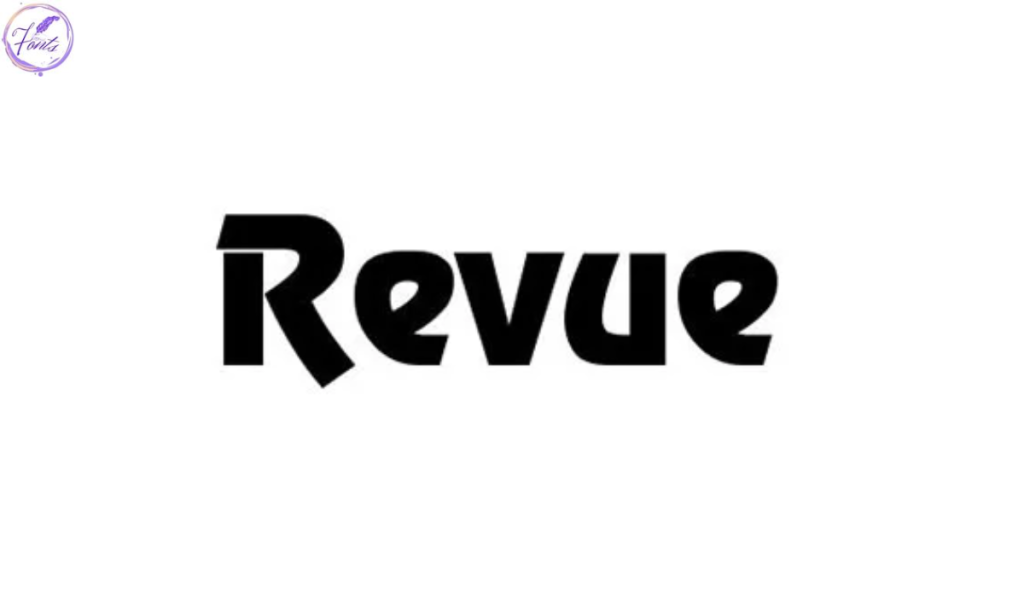
Tác giả: ITC
Ngày phát hành: 2004
Ngôn ngữ: Tiếng Việt, Tiếng Anh, và nhiều ngôn ngữ khác
Bộ Font: Revue
Phân loại: cá tính, độc đáo
Kiểu chữ: sans serif
Revue Font là một bộ font chữ độc đáo và sáng tạo, mang đậm phong cách cổ điển và hiện đại. Được tạo ra bởi đội ngũ thiết kế nổi tiếng là ITC vào năm 2004, Revue Font mang đến sự kết hợp hài hòa giữa các đường nét mềm mại và góc cạnh sắc sảo.